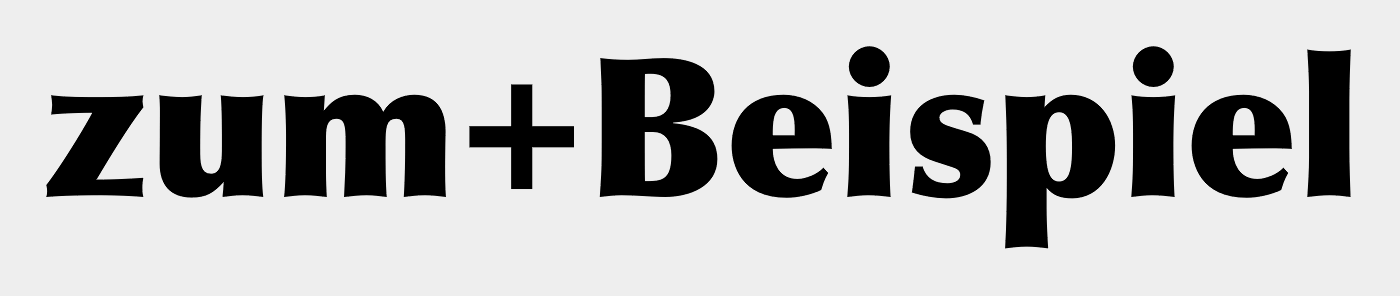
stressed vs unstressed forms
ich lese gerade englische Literatur zu Screendesign / Bildschirmtypografie. Hier bin ich auf die Unterscheidung zwischen "stressed" und "unstressed" forms gestoßen, wofür ich keine deutsche Übersetzung finde.
"Stress
Adding curvature to the straight shapes of a letterform. This is generally not desired
for mobile faces. At best, the small rendered size will simply blur out these subtleties.
It could also make it impossible to render sharp letters at small sizes."
Laut dem Autor sind Unstressed forms; "straight, even-width lines"
Es geht also im Prinzip drum ob und wie die Tangenten verwendet wurden. Bzw ob sich durch die Verwendung von Tangenten eine Kurve zwischen zwei Punkten bildet, was dann "gestresst" wäre, oder ob es sich um eine ungebogene Gerade handelt ("unstressed").
Ich bräuchte hierzu eine korrekte deutsche Definition bzw. deutsche Quellen, die das behandeln, allerdings liefern meine Google-Ergebnisse nur Regeln zu betonten und unbetonten Silben in Gedichten.
hier die bildliche Beschreibung des Autors:
Hab soeben gegooglet und die Definition gefunden:
"Ansatz: (=Kehlung) Mit Kehlung wird der innere Bogen der Serifen bezeichnet. Es gibt welche mit geringer oder starker Kehlung und Serifen ohne Kehlung."
Hab schnell die Lato verunstaltet:
könnte man hier denn auf von Kehlung sprechen? Wenn keine Serifen vorhanden sind?
es geht ja eher um die Biegung des Grundstrichs als um die Biegung des "Serifenbogens" oder? (Entschuldigung für die schwammige Formulierung - bin kein Typo Experte)
Ich bin kürzlich in anderem Zusammenhang darüber gestolpert, habe dann ansatzweise zu verstehen gemeint, was das sein könnte und dann alles zusammen wieder vergessen.
Vielleicht hilft dieser Link, mein Englisch reicht dafür nicht aus, und mein Interesse ist für genaue Übersetzung nicht groß genug.
Falls jemand das versteht und es erklären kann, würde ich dieses Wissen durchaus noch in eine nicht allzu abgelegene Ecke stopfen wollen.
"Ansatz: (=Kehlung) Mit Kehlung wird der innere Bogen der Serifen bezeichnet. Es gibt welche mit geringer oder starker Kehlung und Serifen ohne Kehlung."
Hab schnell die Lato verunstaltet:
könnte man hier denn auf von Kehlung sprechen?
Ähm, nein. Die Kehlung ist nach meinem Verständnis immer eine Einbuchtung, niemals eine Ausbuchtung.
Ansonsten bezeichnet gekehlt eher generell das Vorhandensein einer Einbuchtung – nicht automatisch eine konkrete Stelle eines Buchstabens. Serifen sind dabei sicherlich eine typische Position, aber der Definition »Mit Kehlung wird der innere Bogen der Serifen bezeichnet« kann ich mich also nicht anschließen.
Könnte es sein, dass die Frage Stress oder nicht darauf hinaus läuft: Dynamisch = Stress, Statisch = Unstressed? Wobei eas letztlich egal ist, was zu einem dynamischen Schriftbild führt?
Wenn ich den Artikel beim Überfliegen richtig verstehe, bezeichnet "stress" jede Art von Strichstärkenkontrast, also alles, was beim Anblick einer Schrift als Unterschied (und damit im wörtlichen Sinne "betont" gegenüber einem Vergleichsparameter) wahrgenommen wird. Das bezieht sich vor allem auf die Grundkonstruktion einer Schriftart: hier ist eine klassizistische Antiqua "gestresster" als eine Renaissance-Antiqua oder Serifenlose und eine Kursive "gestresster" als eine Aufrechte. Es bezieht sich daneben auf konkrete Linienführungen: z.B. die Bögen und Rundungen einer (eigentlich recht "ungestressten") Renaissance-Antiqua. Im Ausgangsbeispiel von axum wird der Begriff, wenn ich das spontan recht sehe, im leicht übertragenen Sinne verwendet: Der Autor geht vom Grundsatz aus, dass Serifenlose verhältnismäßig "ungestresst" sind; wann immer man jedoch an den geraden, "ungestressten" Linien etwas Kurviges hinzufügt, erhöht sich der "Stress" und damit die Lesbarkeit in bestimmten Medien (dieser "Stress" im übertragenen Sinne hat nicht immer und automatisch mit Strichstärkenkontrast zu tun, weshalb ich glaube, dass die Verwendung hier nur analog ist). Mir fällt spontan keine gelungene Übersetzung ein, ich vermute aber, man sollte bei der Unterscheidung "gerade" vs. "kurvig" ansetzen, nicht unbedingt bei der wohl verbreiteteren Bedeutung für "stress" im Sinne von Strichstärkenkontrast.